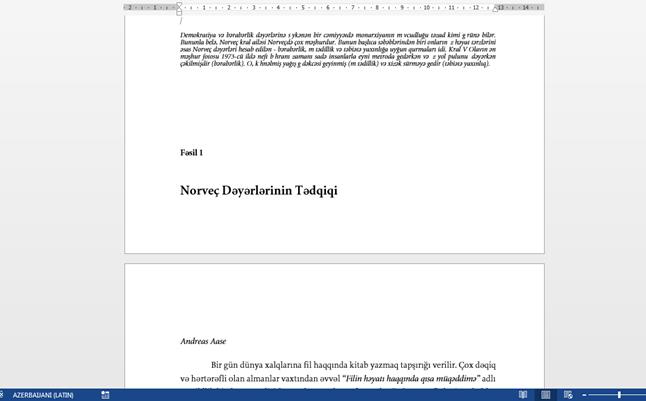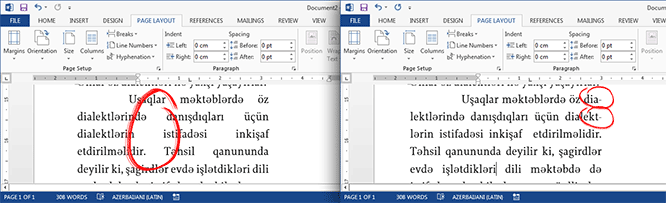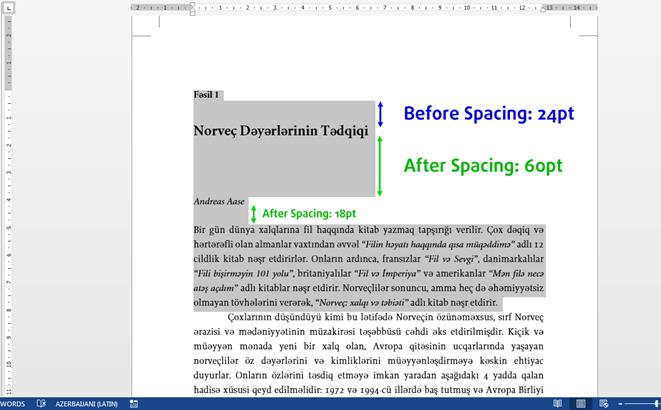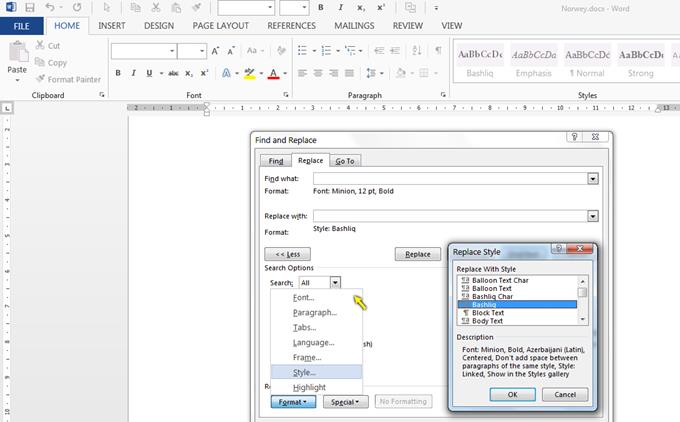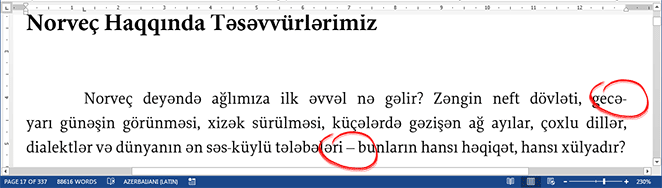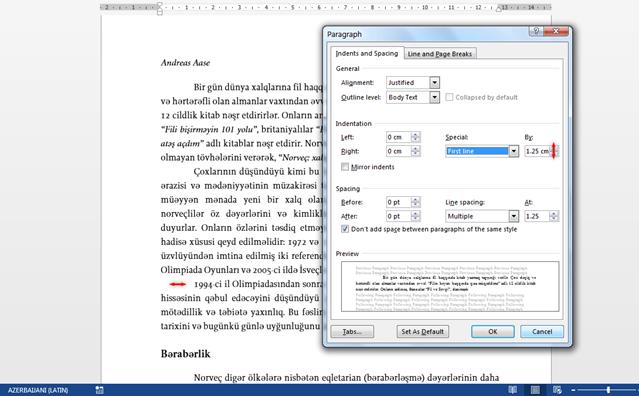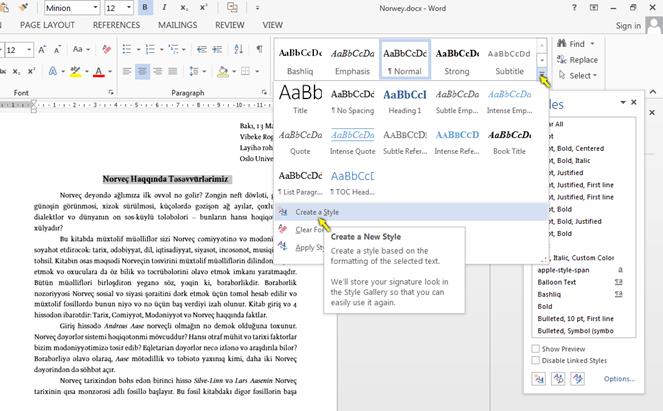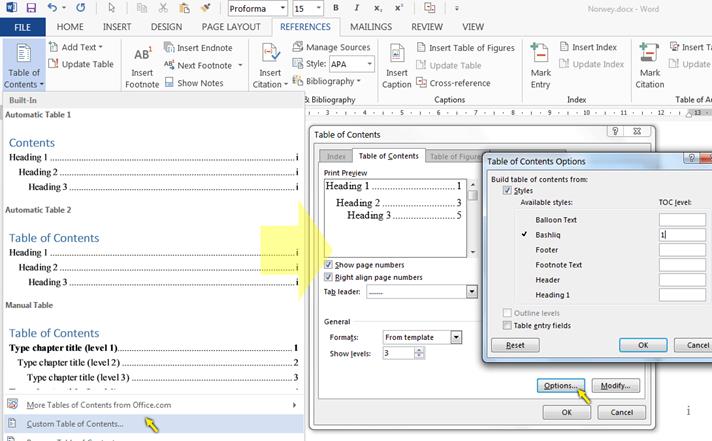
Mətn səhifənin ortasında qurtarıbsa yeni səhifəyə keçmək üçün çoxlu Enter basmaq lazım deyil. Belə olduqda mətnin əvvəlində bir yerdə bir neçə sətir silinsə yeni səhifə artıq yeni olmayacaq. Məsələn, altdakı şəkildəki kimi başlıq tək başına mətndən ayrı səhifədə olduğu üçün çirkin görünəcək.
Belə olmaması üçün Ctrl+Enter basmaqla yeni səhifə əlavə edə bilərik.
Var yeni paragraf, bir də var yeni sətir. Sizə görə hər biri enter basmaqla düzəlir amma Word kimi ağıllı proqramlar sizdən fərqli olmasını istəyir. Enter-i basmaqla əslində siz yeni paraqrafa keçmiş olursunuz. Amma Shift+Enter yeni sətir deməkdir.
Ona görə paraqrafları bir-birindən aşağıdakı kimi aralı etmək istəyiriksə hər birinin arasına iki dəfə Enter basmaq düzgün deyil. Yolu budur ki, mətni seçib, sağ tıqlayıb PARAGRAPH seçirik, sonra SPACİNG bölümündə BEFORE qiymətini 18 filan qoyuruq.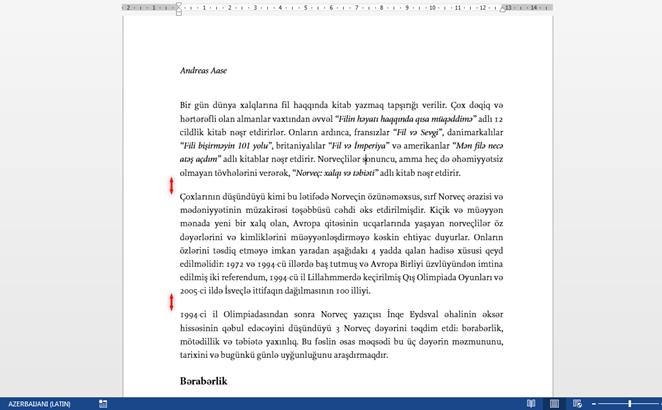
Paraqrafları bir az içəridən başlamaq istəyiriksə ağıllı davranıb Tab istifadə etmək də doğru deyil. Belə ki, burada da mətni seçib PARAGRAPH-dan İNDENTATION bölümündə aşağıdakı kimi ilk sətiri nə qədər içəridən başlatmaq istədiyinizi seçə bilərsiniz:
Bu spacing çox işə yarayır, məsələn, sətir arasına məsafə vermək istəyiriksə yenə də Enter-lə doldurmaq heç düzgün deyil. Aşağıdakı kimi BEFORE – AFTER SPACE-ləri düzəldərək düzgün iş görmək lazımdır.
Tire, iki budaq cümlə arasında və dialoqların əvvəlində olmalıdır. Defis isə tiredən qısa olub, iki rəqəm və söz arasında, heca sonunda ola bilər. Çıxma işarəsi ilə defis eynidirlər. Ona görə defisi (-) klaviaturada tapmaq rahatdır. Tire (–) yazmaq üçünsə Alt düyməsini basılı saxlayıb, klaviaturanın sağ tərəfindəki numeral düymələrlə 0150 yığırıq. (Bax: Başqa nələr yazmaq olar)
İki söz arasında tək boşluq olmalıdır. Nöqtə və vergüldən əvvəl isə boşluq olmamalıdır.
Sətirarası məsafə fontun hündürlüyünün ən azı 120%-i olmalıdır. Daha oxunaqlı yazılar üçün məsafə 130% qəbul edilir.
Məqalə, kitab yazıları kimi uzun mətnlər oxunurkən yorulmamaq üçün Serif fontlara üstünlük verilməlidir. Sans-serif adətən, ekran yazılarında, başlıq və işarə mətnlərində (Exit, Closed kimi) istifadə olunmalıdır. (Bax: Serif və sans-serif fərqi)
Sətirlərin uzunluğunun 45-75 hərf (boşluq daxil) olması oxuma sürətini artırır. Çox uzun sətirlə yazılmış mətnləri oxurkən sətirdən yeni sətirə keçəndə hansı sətirdən davam edəcəyinizi çaşdıra bilərsiniz. İdeal sətir uzunluğu 66 işarə və 11cm-dir.
Azərbaycan dilində şəkilçilərdən bol istifadə edildiyi üçün sözlərin uzunluğu xeyli uzanır. Mətn yanlardan düz - JUSTİFY ediləndə mətndə sözlər arası məsafələr uzanıb, bəzən də alt-alta düşüb boş "pəncərə"lər yarana bilər. Hecalamadan istifadə edərək bunlardan qurtula bilərsiniz. Hecaları bölmək üçün Ctrl+- düyməsini basdıqda adi halda görünməyən, sadəcə sətir sonunda defisə çevrilən işarə əlavə olunur. Word kimi məşhur programlarda təəssüf ki, hələ də azərbaycanca avtomatik hecalama yoxdur (hyphenation).
Uzun sözlərdə hecalama zamanı çalışın yeni sətirə sözün uzun hissəsini ayırın. Məsələn, "cavanlaşdır-ma" kimi yeni sətirə keçirmək yanlış olaraq ilk anda "cavanlaşdır" kimi oxunduğuna görə oxucu cümlənin mənasını itirə bilər. "cavanlaş-dırma" daha məqsədəuyğundur. Bu eyni zamanda yeni səhifə və sütunda qalan mətnin tək sətiri üçün də keçərlidir.
Bir neçə fontdansa, fontun italic və bold tiplərindən istifadə edin.
İnsan özünə indiyənə kimi ən çox verdiyi zülmü “mündəricat” düzəldərkən verməyib. Səhifələri nömrələyirsən, sonra mətndə bir sətir ora-bura dəyişiklik edən kimi mündəricatda bütün rəqəmləri gərək təzədən düzəldəsən. Halbuki, işi əvvəlcədən görəndə Word avtomatik sənə mündəricat düzəldə bilir.
Bunun üçün gərək mündəricatda görünməsini istədyin başlıqların hamısını tək stil adı altında düzəldəsən. Məcbur deyil ki, hamısı eyni stildə (bold, italic və font ölçüsü və s) olsun. Vacibdir ki, eyni stil ADInda olsun.
Belə edirik: istədiyimiz başlığı tapıb seçirik, sonra yeni STYLE yaradırıq:
Sonra stilin adını yazırıq və bundan sonra yazacaqlarımız bütün başlıqları bu stildə edirik (başlığı seçib, menyudan yeni ad verdiyimiz stili seçərək).
Əgər iş-işdən keçibsə, başlıqlar əvvəlcədən yazılıbsa onda Ctrl+H basaraq FORMAT bölümündən başlıqlarınızı hansı şiriftdə, bold-lamı, italic-ləmi, hansı ölçüdə yazmışdınızsa onu axtarıb, REPLACE WITH bölməsinə də yeni yaratdığınız stili seçirsiniz. Və REPLACE ALL basırsınız:
Bütün başlıqlar eyni stildə olduqdan sonra mündəricatı yaratmaq üçün menyudan REFERENCES > TABLE OF CONTENTS > CUSTOM ... > OPTIONS -dan öz düzəltdiyimiz başlıq stilimizi TOC 1 level edirik. Aşağıdakı kimi:
Son olaraq qeyd edim, mündəricatın yenilənməsi üçün ya arada bir, vəya kitabı təhvil verməmişdən əvvəl mündəricat cədvəlinin üstünə sağ tıqlayıb UPDATE FİELD etməyi unutmayın. Bu zaman cədvəlin sadəcə səhifə nömrələrinimi, yoxsa başdan-ayağa təzələnməsini seçə bilərsiniz.
İkinci qısa bir varyant da başlıqları seçib, ya sağ mouse düyməsi ya da menyudanPARAGRAPH > OUTLINE LEVEL u mündəricatdakı səviyyələrə uyğun səviyyəni seçirik. Ən azından Level 1 seçmək lazımdır. Bir alt başlıq varsa Level 2, daha kiçik alt başlıq üçünsə də Level 3 və s. Geri qalan mətn isə standart olaraq Body Text olaraq seçili olur. Artıq səviyyələr müəyyən olduqdan sonra mündəricat cədvəlini əlavə etmək istədiyiniz yerə REFERENCES > TABLE OF CONTENTS-dən əlavə edə bilərsiniz.
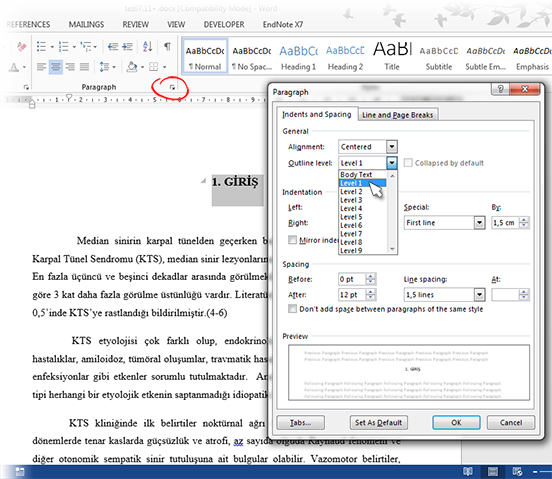
Burada da xatırladıram ki, mündəricatın yenilənməsi üçün ya arada bir, vəya kitabı təhvil verməmişdən əvvəl mündəricat cədvəlinin üstünə sağ tıqlayıb UPDATE FİELD etməyi unutmayın. Bu zaman cədvəlin sadəcə səhifə nömrələrinimi, yoxsa başdan-ayağa təzələnməsini seçə bilərsiniz.